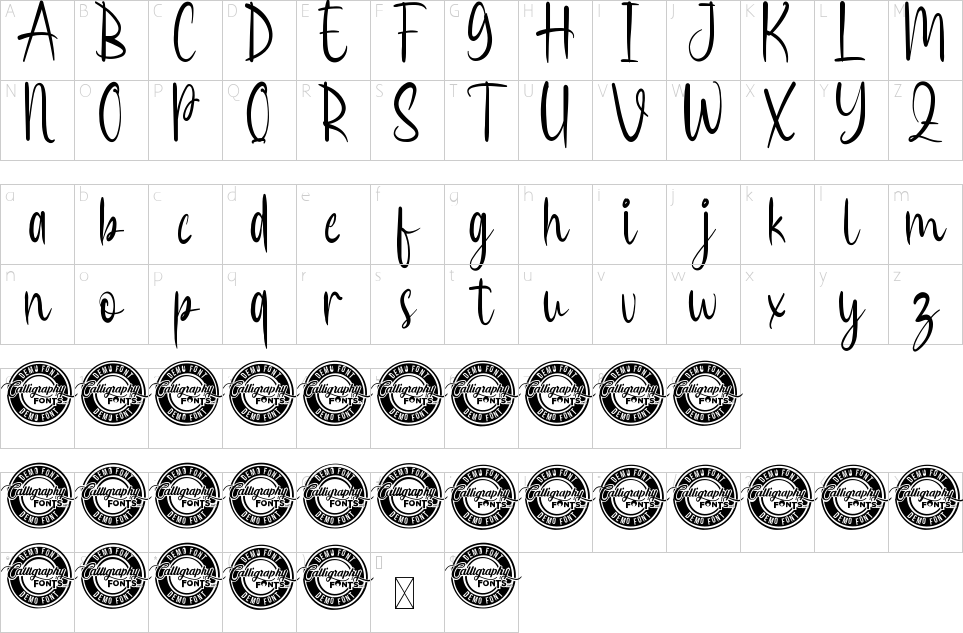
Descubra a fonte perfeita para seus projetos com Jossie Blessyn. Desenvolvida por CalligraphyFonts, esta fonte única foi projetada para fornecer um toque personalizado e elegante a qualquer projeto de design. Jossie Blessyn é uma criação sofisticada que se destaca por sua forma arredonda e elegante, tornando-a uma escolha inteligente para textos de marketing, design editorial e até mesmo para gráficos de logotipo. Com seu design cuidadosamente elaborado por um designer de grafismo, Jossie Blessyn oferece uma experiência de escrita excepcional, destacando-se entre as centenas de fontes disponíveis gratuitamente na nossa plataforma. Aproveite esta fonte única, que tem sido baixada 1,764 vezes, para adicionar um toque diferenciado a seus projetos de design.